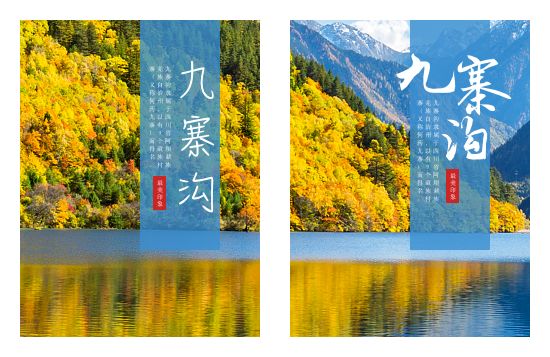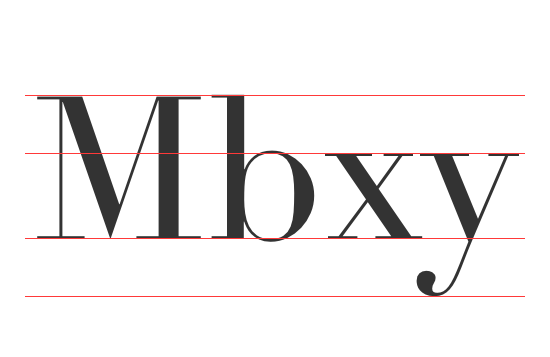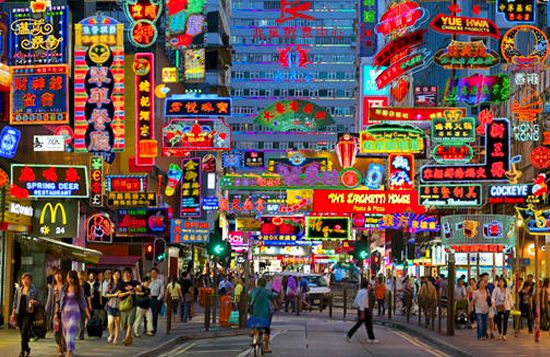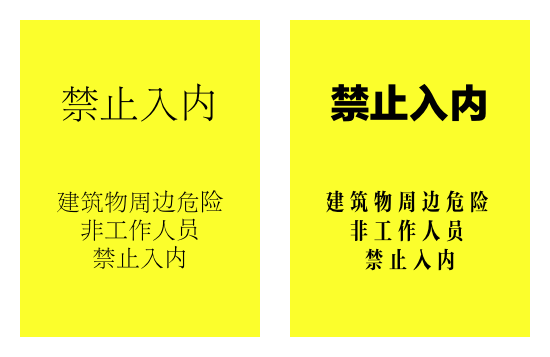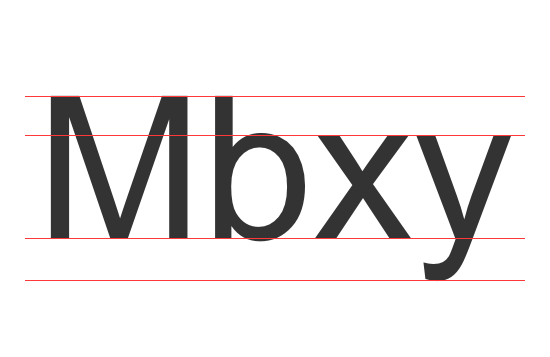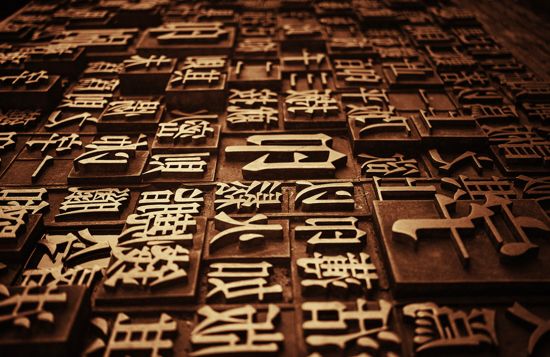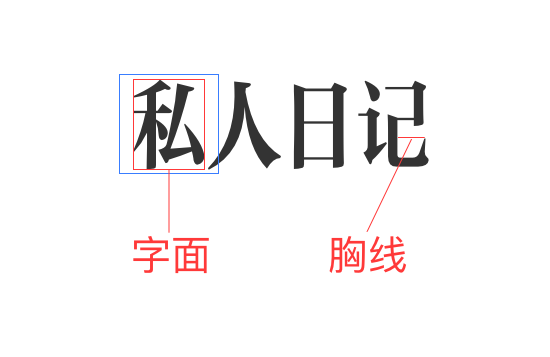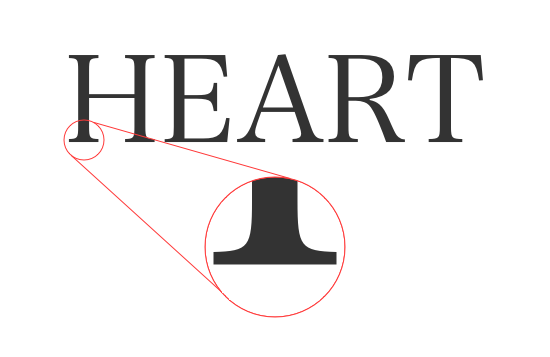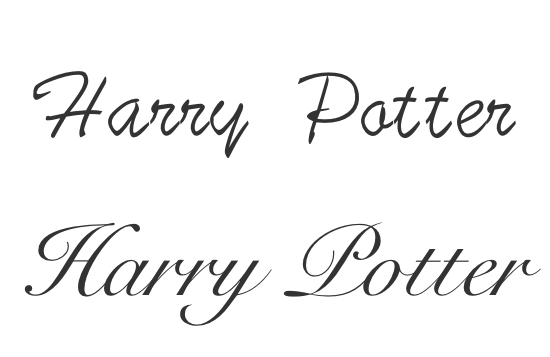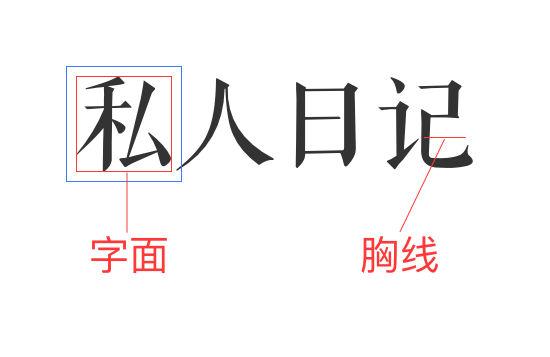
初识东西方语系文字,配合设计上的色彩、版式等,来对文字的设计使用上予以解读
在我们的设计工作中,“图像”和“文字”的重要性无须多言。无论是平面设计、电商设计、还是UI设计,这些都离不开文字。
但是文字却又一直处于“不被重视”的状态,特别是互联网的兴起,人们在设计作品的时候,几乎不太会深思,而只以“用计算机中的字体设计”进行制作。
在计算机普及之前,我们的文字设计颇具匠心,更早之前的活字印刷更是设计的瑰宝。而计算机的出现无疑让“文字”的设计选择性更多,当然大家也都不再关注字体设计上的可能性了。
本文将设计中的“文字”部分单独提取出来,配合设计上的色彩、版式等,来对文字的设计使用上予以解读。
虽不能概括所有文字的前世今生以及各种使用技巧,但我们相信,这篇文章会让你对设计中的“文字”有更进一步的认识。
// 文字与设计 //
我们每天都会接触到文字,但是,真正仔细研究文字的外部形态、精通文字设计的人却很少。
以中国来说,从商周时代开始,发展到隋唐时期的雕版印刷,宋代时出现的活字印刷,一直发展到现代的数字影像......
而文字与图像也有着紧密的关联性,因此,要将它们视为一体来认识。
在很多的设计作品中,文字并非只是客观的传达信息,文字设计本身也能够表现出强烈的情感和力量。
文字的设计注重“字体”的设计,字体各式各样,有的给人严肃印象的,也有看起来让人觉得轻松自在的。即使在同样的文章,使用不一样的字体,观者也会有不同的感受。
我们常提到设计要“易于传达”,而当语言文字无法完全表现出“感觉”时,就必须要选择适合的字体来表现来。
在理解文字之前,我们要首先来认识文字的构成要素中每个部位及其名称。
▐ 首先来看看西方语系文字的结构:
西方语系文字是以4条水平线为标准的文字构造,第三条水平线是用来当作标准的“基线”,西方语系文字几乎都是写在这条基线之上的。
随着文字设计的不同,平行线的位置也会跟着改变,从而形成各自的特色。
以小写字母“x”的高度为“x高”,“x高”决定这套字体的整体大小,小写字母的高度的平均发布也会影像文字的阅读。
像是“C”“O”这个类的字母中间的空间被成为“字腔”。字腔较宽的字体就会给人开放、轻松的感觉,相反,字腔较窄的字体就会感到非常密集,也会感觉更有力量。
▐ 接下来看看东方语系文字的结构:
我们都在田字格上写过文字,用格子来理解东方语系文字是最易懂的。
格子分为“虚拟框”和“字面尺寸”,“字面尺寸”也会随着不同的字体而有所变化。
东方语系文字的基础在于文字的骨架,我们称之为“胸线”,胸线小的字体看起来更加匀称,整齐一致,也能更好的传达出传统的感觉。
而胸线大的字体则更加易读,更具现代感。
除了“骨架”之外,还有就是文字的“血肉”了,我们称为“点”和“勾”。它们决定了设计文字字体的特色所在。
介绍完文字的结构,我们接下来具体看看西方语系文字和东方语系文字的分类。
在西方语系文字中,字形笔画前端有像是爪形的装饰,我们称之为“衬线体”。
根据衬线体线条宽度的差距,我们可以分为“旧体”和“现代体”。
旧体类似于用笔尖压平的毛笔书写文字,在起笔出保留了书写痕迹,能让人感觉到传统的亲切感,整体更易于阅读。
外形特点激素笔尖会留下固定的倾斜角度,像“O”这个字母较细的部位会出现从左上至右下的角度。
现代体则属于比较工整的风格,体现了明快的现代感,给人以冷峻、严格的印象。
外形特点上,线条的宽度变化相当明显,像“O”这个字母呈现上下垂直的样子。
此外,衬线体文字根据衬线变化大致可以分为“支架衬线体”、“发丝衬线体”、“板状衬线体”。
▐ 支架衬线体是旧体中最常见的字型,其特点是衬线部分为弧形。这种字体能够表现出温柔亲切的传统风格。除了衬线部分之外都是直线,在传统中仍能使人感受到现代感。
▐ 发丝衬线体是现代体常见的字型,衬线部分由细直线构成,其特点是看起来非常平整。粗细线条的对比非常清晰、明确,具有现代感。
▐ 板状衬线体的衬线部分为粗厚的四角形。这类型的字体看起来强劲有力,多用在标题处,具有怀旧的气氛。
无衬线体和东方语系文字的黑体很类似,无衬线体是由衬线体中的“版状衬线体”发展而来的。
无衬线体比衬线体的“x高”更大一些,整体上看内容较多的文字,会觉得整篇又黑又重。
▐ 古典型的无衬线体,适用于大尺寸的标题文字,具有及其抢眼的效果。表现处古典式男性勇猛粗旷的形象。
▐ 现代感的无衬线体,展现明快的感觉。这类字体没有多余的装饰部分,呈现处几何风格,给人留下理性、冷静的印象。多用于杂志和目录的设计。
除了衬线体和无衬线体,还有很多的其它字体,这边我们就简单介绍下具有代表性的几种字体。
▐ 首先是被成为“哥特体”的字体,运用笔尖扁平的笔书写,传达出庄严感,也有一种令人敬畏的高贵感。
▐ “手写体”是一种充满变化的字体,每个人都风格都不一样。现代风格的手写体给人温暖的感觉,正如自己亲手写下的文字。
▐ 另外,还有一种被称为“装饰体”的文字,这种字体的出现都是为了顺应当时的潮流,不管什么时候,看到之类的字体都能感受到那个年代的风格。
竖线粗、横线细,在笔画结束处有一个类似三角形、名为“鳞”的装饰,这种字体称为“宋体”。
宋体是大家最熟悉的一种字体,在大量的书籍上都有它的身影,它不仅经常被使用在正文部分,也经常出现在标题上,是一种很基本的字体。
宋体也分为“传统型宋体”和“现代型宋体”。
▐ 传统型宋体“胸线”和“字面”都比较狭小,笔画的粗细差异大,像是用笔书写出来的效果。
▐ 现代型宋体“胸线”比较大,笔画宽度差异较小,起点和终点是如同几何形般的刚硬线条,赋予了字体明快的现代感,也增添了冷峻的感觉。
▐ 现代型宋体缺乏温暖的感觉,而传统型宋体又给人太沉闷的印象,所以取两者所长而设计处了“中间型宋体”。
横线和竖线宽度几乎相同的东方语系字体称为“黑体”。
在早期的印刷时候,正文一般使用宋体,而为了强调标题部分,于是逐渐发展出了强而有力、线条粗壮的黑体。
根据文字的骨架和构成要素来看,黑体也可以分为“传统型黑体”和“现代型黑体”。
▐ 传统型黑体的“字面”和“胸线”都较小,给人凝聚内敛的印象。而字体的线条也并非单纯的直线,仔细看你会发现线条中间部分比较细,两端逐渐变粗。
▐ 现代型字体的“字面”和“胸线”较大,给人开放的印象。线条呈现强烈的水平和垂直感,不必要的线段都被除去,给人一种机械般的感觉。
// 东方语系字体 —— 其他字体 //
除了宋体和黑体之外,还有很多其它的字体,我们接着介绍几种具有代表性的字体。
▐ “楷书”是指书写出来的字体,其文字结构完全没有被破坏,给人一种亲笔写出来的正式感觉。也正是由于太过“正式”,一般用在企业设计或者重要场合。
▐ “行书”属于快速书写的“楷书”,笔画简化了,使得文字较不易阅读。没有过于的庄重感,能够表现出优美的古雅韵味。
▐ “圆体”是指将“黑体”的笔画两端变成圆角,呈现温柔可爱的感觉。经常出现在儿童相关设计种。
▐ “书法字体”是我们最具有代表性的字体,充满了自由创作的意识,具有强烈的个性,在设计上非常有特点。
// 字体家族 //
一套文字除了字体大小的区分,还有一种概念叫“字重”,学名为“腰线”,通俗理解就是字体的粗细。
一般标准的粗细我们称之为"regular",在粗就是"medium",更粗的文字就被称为"semibold"。
而往细了就有"light""Thin""uitralight"的区分。
在很多中文字体中,按照“腰线”使用“W6”这种标注方式,数值越大,腰线差异越大。
// 小 结 //
我们只有在充分理解字体的基础上,在设计时准守文字相关的规则,这样才能更加自由的使用字体。